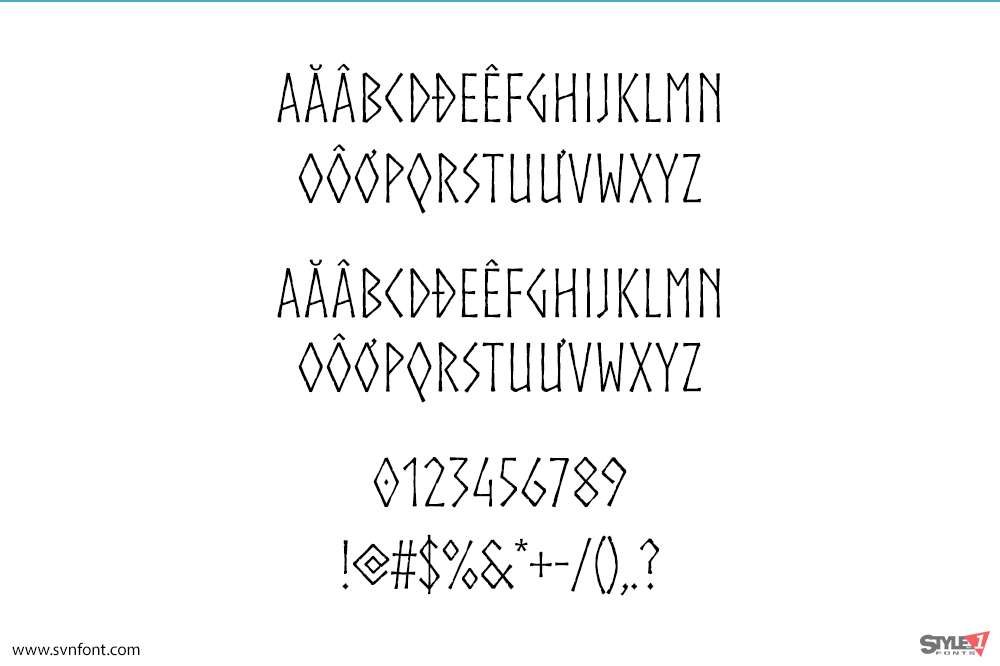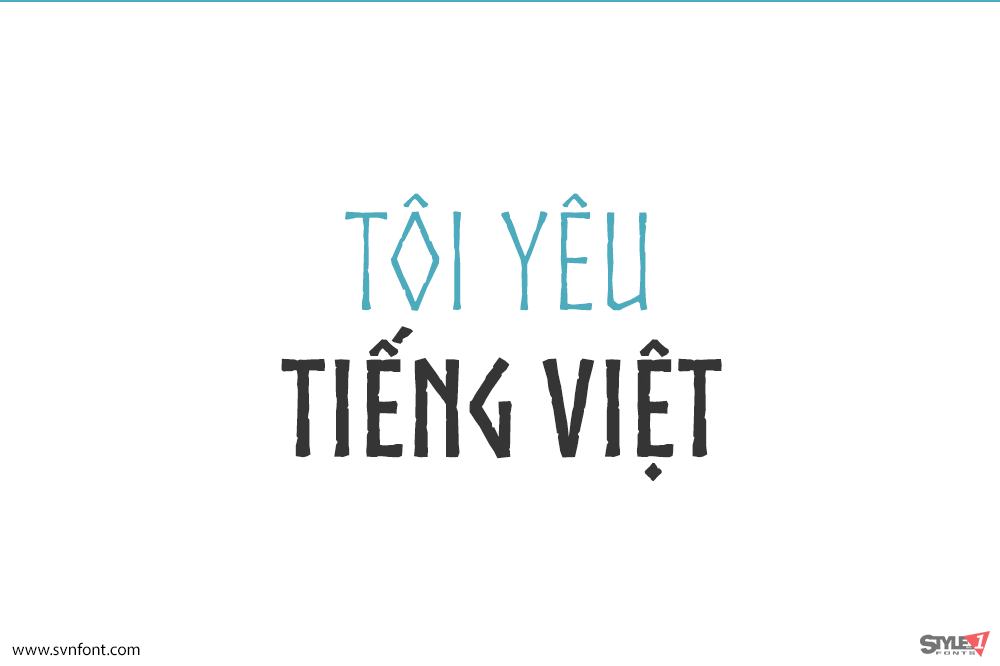
Bảng chữ cái Rune là hệ thống ký tự từng được dùng để viết nhiều ngôn ngữ German cổ trước khi bảng chữ cái Latin được chấp nhận rộng rãi. Sau khi Latin trở nên phổ biến, chữ Rune vẫn tiếp tục được sử dụng cho những mục đích chuyên biệt. Bên cạnh đó, nhiều font hiện đại đã được phát triển, lấy cảm hứng từ hệ chữ Rune — trong đó có Norse, typeface được giới thiệu hôm nay.
Đây là một display font do Joël Carrouché thiết kế, lý tưởng nếu bạn đang tìm kiếm một font độc đáo cho các chủ đề liên quan đến huyền thoại và truyền thuyết trong phim ảnh, truyện kể, trò chơi điện tử, chương trình TV, tạp chí hoặc thiệp mời. Font có thể tải miễn phí và sử dụng cho cả dự án cá nhân lẫn thương mại.
Nhà thiết kế: Joel Carrouche